Icône
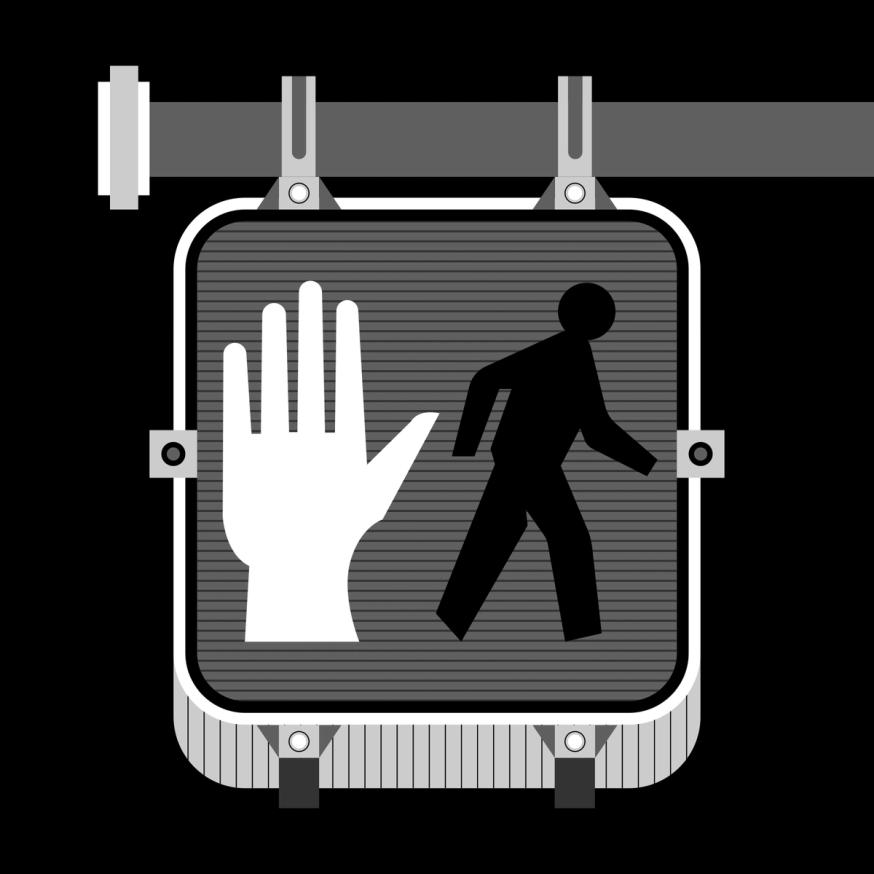
En typographie et en dessin de caractères, un icône peut être un pictogramme (dessin stylisé d’un objet) ou un idéogramme (dessin ayant une signification).